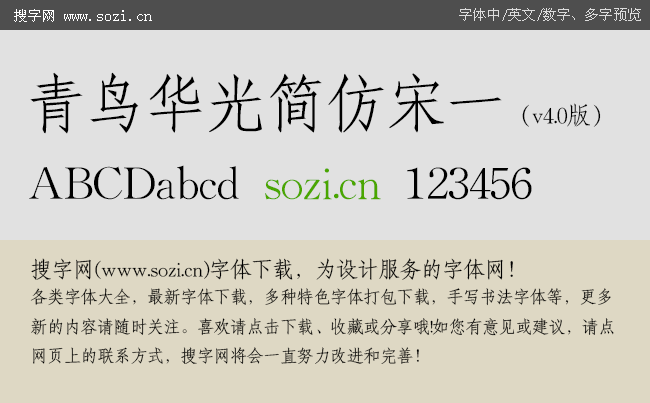
青鳥華光簡仿宋一
搜字網(wǎng)提供一款青鳥華光簡仿宋一中文字體下載,青鳥華光簡仿宋一是一款字形清秀的中文字體,該字體結(jié)構(gòu)優(yōu)美,識別性好,常用于產(chǎn)品設(shè)計、包裝印刷、報刊雜志、正文標(biāo)題、繪畫創(chuàng)作等廣告設(shè)計場合使用。